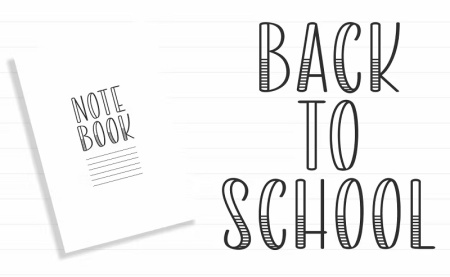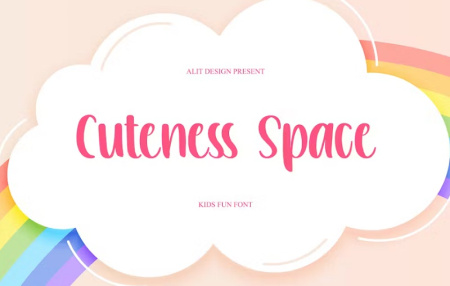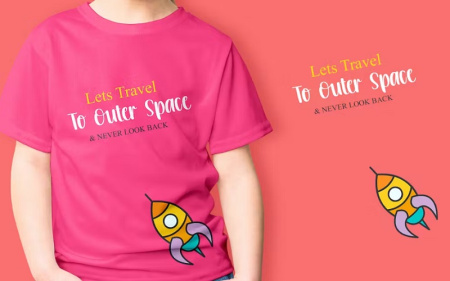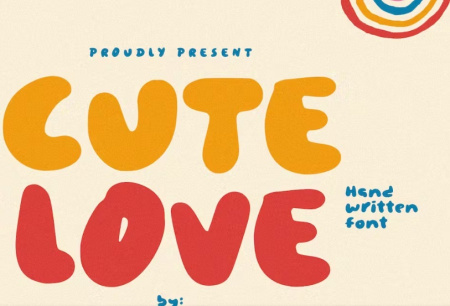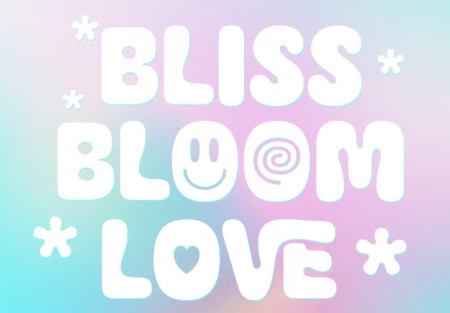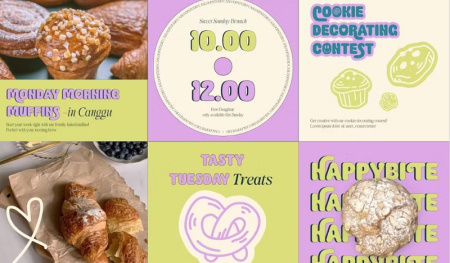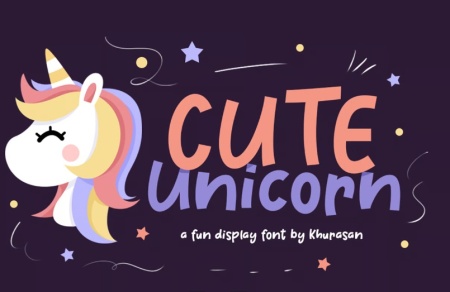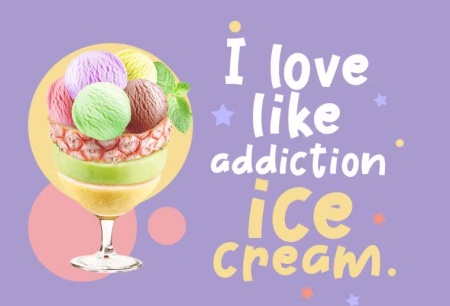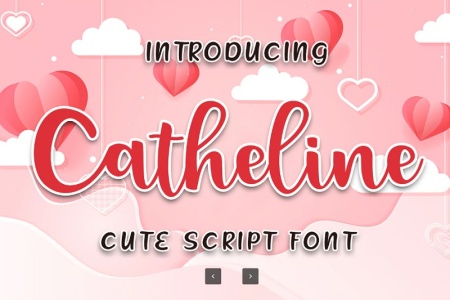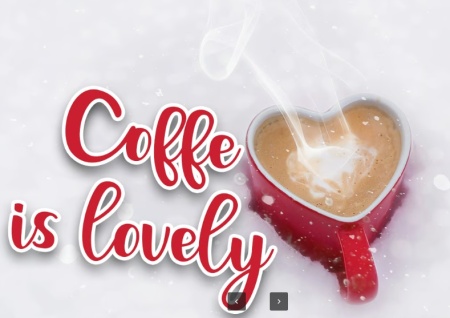
فونت انگلیسی کیوت شامل 7 فونت کیوت انگلیسی از جی اف ایکس دانلود می باشد. فونت انگلیسی کیوت زیبا مناسب برای نیازهای پروژه طراحی شما است، شما می توانید برای طراحی با موضوعات تم های مدرسه، تم های فارغ التحصیلی، پست های رسانه های اجتماعی، نقل قول ها، پوشش روی تصاویر، لوگوی برچسب ها، پوسترها، نیازهای چاپی، بنرهای وب سایت و موارد دیگر از این فونت استفاده نمایید. برای دانلود فونت به ادامه مطلب مراجعه نمایید.
2- دانلود فونت انگلیسی کیوت Cuteness Space
فونت انگلیسی کیوت Cuteness Space با الهام از طراحی کودکانه شاد، بامزه و بسیار زیبا می باشد. این فونت برای طرح هایی با تم های کودکانه، به خصوص زمانی که با رنگ های روشن ترکیب شود عالی است.
3- فونت های کیوت انگلیسی Cute Love
این فونت انگلیسی کیوت مناسب برای امور طراحی ها کودکانه، شاد و بامزه می باشد. این فونت با فرمت های otf-ttf-woff موجود می باشد.
4- فونت انگلیسی کیوت فانتزی Bliss Bloom
فونت انگلیسی فانتزی و کیوت Bliss Bloom از جدیدترین سری فونت های کیوت انگلیسی می باشد. انتخابی عالی برای پروژههای کودک محور، طراحی لوگو، بسته بندی و ... می باشد.
5- فونت انگلیسی کیوت برای اینشات
فونت Cute Unicorn یک فونت کیوت مدرن و سرگرم کننده است. این فونت انگلیسی کیوت برای اینشات، فتوشاپ و سایر نرم افزار ها سازگاری دارد. مناسب برای لوگو، برند تجاری، کارت تبریک، پوستر و هر طرحی که ایجاد می کنید.
6- دانلود فونت انگلیسی کیوت و بامزه Catheline
Catheline یک فونت بامزه انگلیسی است که می تواند برای طرحهایی با تم کودکانه، برندهای محصولات غذایی، کارتهای تبریک و هر چیزی که نیاز به ایجاد حس شادی و نشاط دارد، استفاده شود.
7- فونت اسم کیوت انگلیسی
Jacklyn Cute نام این فونت انگلیسی کیوت با طراحی بامزه و ظاهری دوستداشتنی، بازیگوش و کودکانه هست. فونت اسم کیوت انگلیسی مناسب برای طراحیهای مرتبط با کودکان، رندهای محصولات کودکانه، کارتهای تبریک، پوسترهای جشن تولد و غیره می باشد.